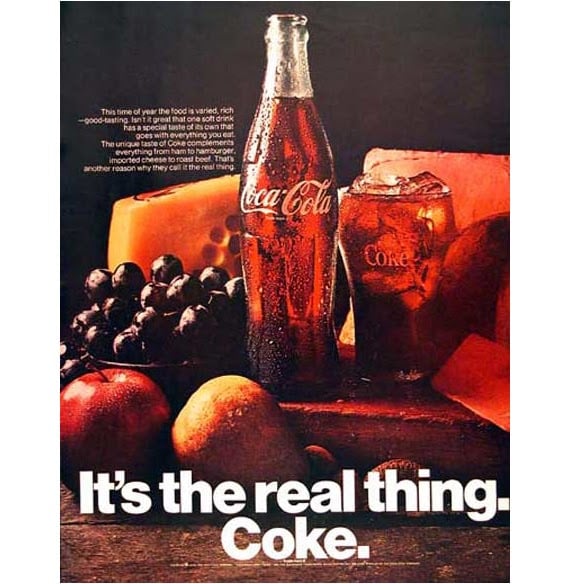
Helvetica: storia di uno dei font più amati dai brand
C’è chi lo ama e chi lo odia: l’Helvetica è uno dei font più utilizzati al mondo, sia in ambito pubblicitario ed editoriale che nella segnaletica urbana. A cosa deve il suo successo e la sua diffusione così pervasiva, e come è cambiato nel corso degli anni?
In questo articolo partiremo dalla sua invenzione, nel lontano 1957, per ripercorrere le tappe che lo hanno portato, attraverso i vari restyling, a diventare il carattere tipografico preferito da molti brand internazionali.
Le origini del font Helvetica
Come suggerisce il suo stesso nome, l’Helvetica nasce in Svizzera, quando Eduard Hoffmann, direttore della fonderia Haas di Münchenstein, decide di commissionare la creazione di un nuovo font al disegnatore freelance Max Alfons Miedinger. L’intenzione di Hoffmann era quella di contrastare il successo dell’Akzidenz Grotesk, il carattere lanciato dalla tipografia concorrente H.Berthold AG.
Fu così che nel 1957 Miedinger propose un nuovo set di caratteri, battezzandolo con il nome Neue Haas Grotesk. Si trattava di un font sans serif (senza grazie) dal design lineare, essenziale ed elegante, che proprio per la mancanza di fronzoli risultava molto leggibile.
Dal punto di vista tecnico, il Neue Haas Grotesk presentava alcune peculiarità, come l’equilibrio tra lo spazio negativo (bianco) che circonda le lettere e quello delle linee che le compongono. Inoltre si sviluppava sempre in direzione orizzontale o verticale, mai in diagonale, per un effetto visivo “deciso” e al contempo neutro.
Mike Parker, l’uomo che cambiò il destino di Helvetica
È il 1959 quando Mike Parker diventa direttore della Mergenthaler Linotype Company. La società americana commercializza la macchina tipografica Linotype, la prima a consentire la composizione automatica delle linee di caratteri. Incaricato di ampliare la libreria di font di proprietà dell’azienda, dal 1959 al 1981 Parker riuscirà ad aggiungerne quasi un migliaio, in molti casi adattando dei caratteri già esistenti alle esigenze tecniche delle macchine Linotype.
Nel 1960 Parker sceglie di adottare anche il Neue Haas Grotesk, incaricando Arthur Ritzel, designer di D. Stempel AG – azienda tedesca partner della Lynotype Company – di ridisegnare e sviluppare la famiglia di caratteri. Il nuovo font viene ribattezzato Helvetica, dal latino Helvetia, Svizzera.
Da quel momento in poi, diventerà un’icona del design svizzero, considerato all’epoca un modello di sobria eleganza e funzionalità, e apparirà in moltissimi manifesti pubblicitari e cartelloni stradali europei e statunitensi degli anni Sessanta e Settanta.
La mappa della metro di New York
Verso la fine degli anni Sessanta, l’Helvetica viene scelto dai designer Massimo Vignelli e Bob Noorda per realizzare la nuova segnaletica della metropolitana di New York e il Graphic Standards Manual, uno dei manuali d’identità visiva più celebrati nella storia del graphic design. L’uso di questo font resterà uno dei marchi di fabbrica di Vignelli: una scelta che contribuirà ad aumentare notevolmente la fama internazionale di questo carattere.
Il primo restyling e l’ingresso nel mondo digitale
Nel 1983 esce il Neue Helvetica, una versione aggiornata del font a opera dello studio grafico Linotype. Vengono introdotti una maggiore spaziatura tra i numeri e dei segni di punteggiatura più evidenti, allo scopo di migliorarne la leggibilità.
L’anno successivo, Steve Jobs decide di introdurlo tra i caratteri presenti all’interno del primo Macintosh, aprendo la strada alla diffusione della versione digitale del carattere tipografico.
Il font più amato (e odiato) dai designer
Qual è stata la ragione del successo di questo carattere? Indubbiamente la sua versatilità, l’aspetto moderno e l’eleganza discreta, che lo rendono adatto sia a un manifesto pubblicitario che a un manuale di istruzioni, così come a un catalogo d’arte.
D’altro canto, la sua onnipresenza nel mondo dell’editoria e della grafica pubblicitaria ha suscitato varie critiche, ed è diventata sinonimo di omologazione. Uno dei suoi detrattori è Bruno Maag, type designer svizzero proprietario della Daalton Maag, la fonderia londinese che ha realizzato font per aziende come Lush, Nokia e HP.
In un’intervista pubblicata sul sito Eye on Design, Maag critica l’ubiquità del font: «I designer usano l’Helvetica per pigrizia. E anche perché è una scelta sicura. Il risultato è un’omogeneità presente in tutti i progetti grafici di brand identity che si vedono in giro.»
In effetti, questo carattere è ancora utilizzato nelle campagne di comunicazione di moltissime aziende, oltre che nei loro loghi. Qui citiamo solo alcuni nomi tra i tanti: Lufthansa, Nestlé, Panasonic, Microsoft e celebri case automobilistiche come BMW e Jeep. Inoltre, la sua versione digitale è impiegata nelle interfacce utente delle piattaforme social Facebook e Instagram.
Nel 2007, in occasione del 50° anniversario dalla sua invenzione, il font è diventato protagonista di un film documentario dal titolo “Helvetica” diretto da Gary Hustwit. Nello stesso anno gli viene dedicata la mostra “50 years of Helvetica” presso il Museum of Modern Art di New York.
Helvetica Now è disponibile in 3 versioni: Micro per gli schermi piccoli, Text per il testo normale e Display per i formati più grandi. Ogni dimensione è offerta in pesi che vanno dalla linea sottile al nero extra, per un totale di 48 pesi. Le forme dei caratteri appaiono più distanziate e leggibili anche su dispositivi elettronici di piccole dimensioni.
Il rilascio di questa nuova versione ci fa pensare che il futuro di Helvetica sia ancora lungo e tutto…”da scrivere”!